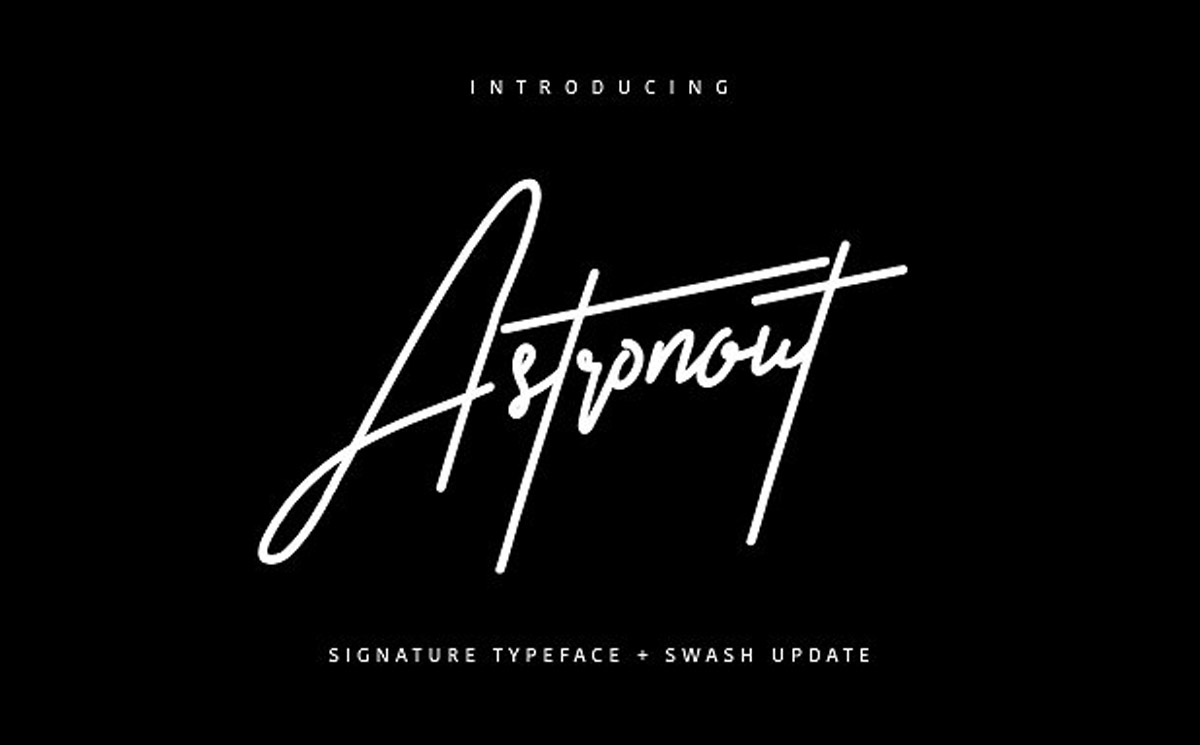
Font chữ viết tay Việt hóa SVN Astronout
Font chữ viết tay Việt hóa SVN Astronout – Nét chữ mềm mại, tự nhiên và đầy cảm xúc
SVN Astronout là font chữ viết tay (Handwritten Script) được yêu thích nhờ những nét bút mềm mại, tự nhiên và giàu cảm xúc. Sau khi được Việt hóa đầy đủ dấu tiếng Việt, font mang đến trải nghiệm sử dụng hoàn hảo cho các nhà thiết kế, content creator và người làm in ấn khi cần tạo nên những sản phẩm mang phong cách gần gũi, nghệ thuật.
Với thiết kế thanh thoát, các ký tự được nối liền một cách uyển chuyển, SVN Astronout phù hợp với nhiều phong cách thiết kế từ hiện đại đến vintage. Font giúp truyền tải cảm giác chân thật, tinh tế và tạo điểm nhấn cho mọi ấn phẩm.
Đặc điểm nổi bật của SVN Astronout
• Thiết kế chữ viết tay tự nhiên, mềm mại và dễ đọc.
• Hỗ trợ đầy đủ tiếng Việt với hệ thống dấu được Việt hóa chuẩn.
• Đường nét thanh lịch, phù hợp cho thiết kế sáng tạo.
• Có thể kết hợp với các font Sans Serif hoặc Serif để tạo bố cục hài hòa.
• Thích hợp cho cả thiết kế in ấn và nền tảng kỹ thuật số.
Ứng dụng của font SVN Astronout
Nhờ phong cách viết tay nhẹ nhàng, SVN Astronout được sử dụng rộng rãi trong nhiều lĩnh vực thiết kế như:
• Thiết kế logo thương hiệu.
• Tiêu đề poster, banner quảng cáo.
• Thiệp cưới, thiệp sinh nhật, thiệp mời.
• Bìa sách, bìa album, tạp chí.
• Chữ ký cá nhân hoặc watermark.
• Thiết kế quote truyền cảm hứng.
• Nội dung mạng xã hội, YouTube Thumbnail và Pinterest.
• Bao bì sản phẩm thủ công, mỹ phẩm hoặc thời trang.
Đây là lựa chọn phù hợp nếu bạn muốn tạo cảm giác thân thiện, tinh tế và mang dấu ấn cá nhân trong mỗi thiết kế.
Kết luận
Nếu bạn đang tìm kiếm một font chữ viết tay đẹp, mềm mại và hỗ trợ tiếng Việt đầy đủ thì SVN Astronout là lựa chọn rất đáng trải nghiệm. Với phong cách tự nhiên, giàu cảm xúc và khả năng ứng dụng đa dạng, font phù hợp cho cả thiết kế chuyên nghiệp lẫn các dự án cá nhân.